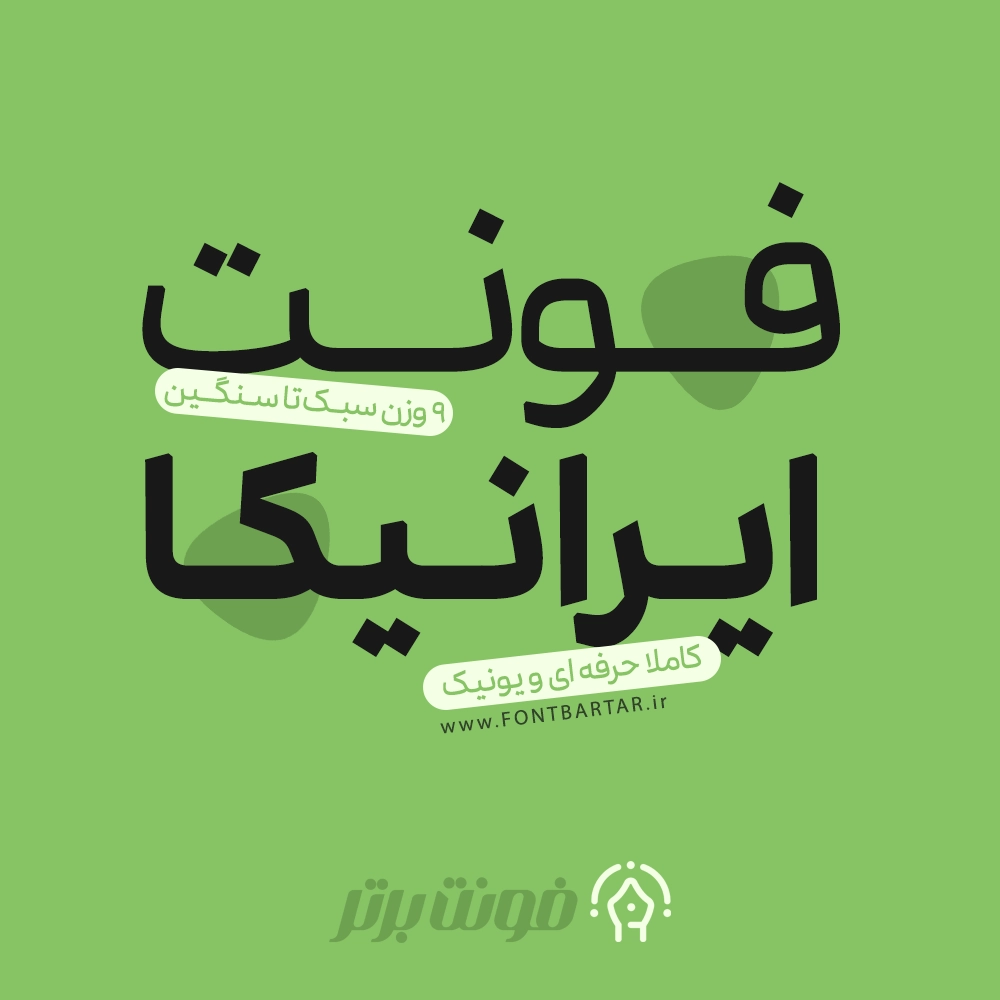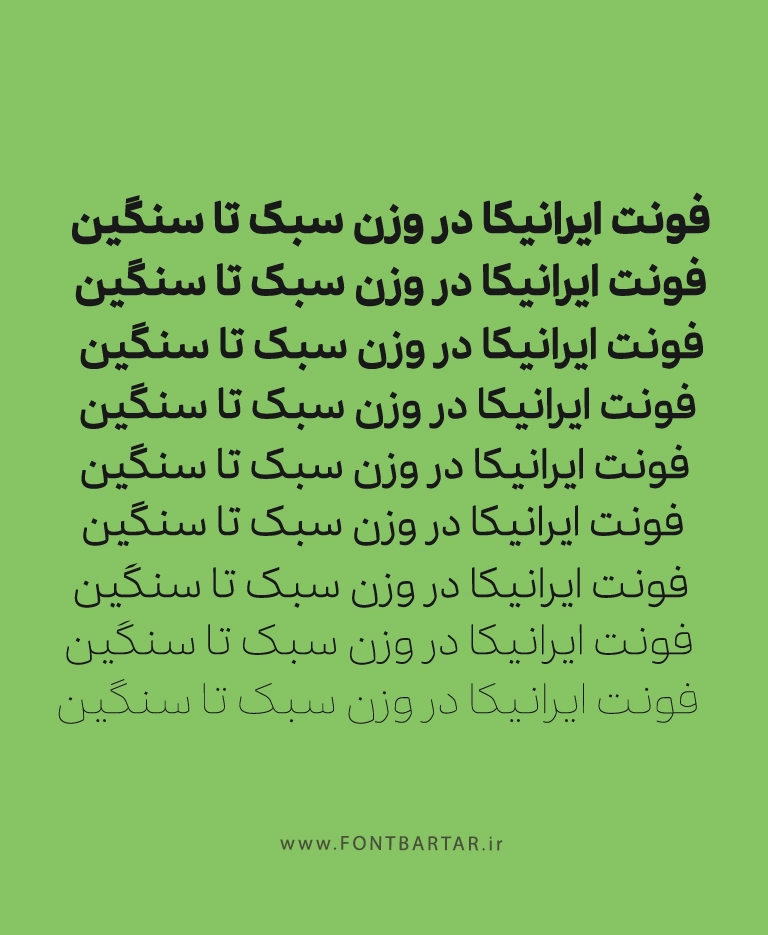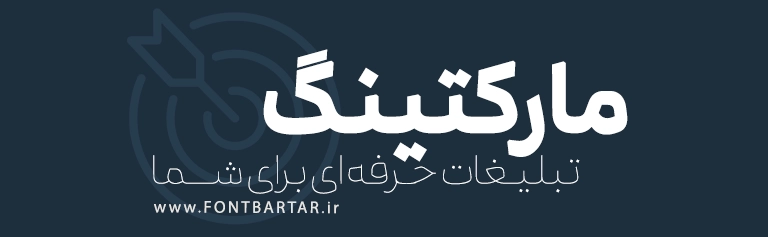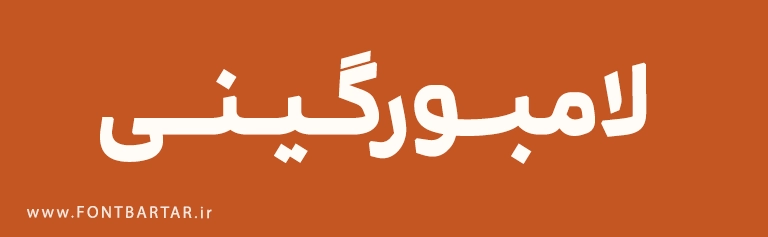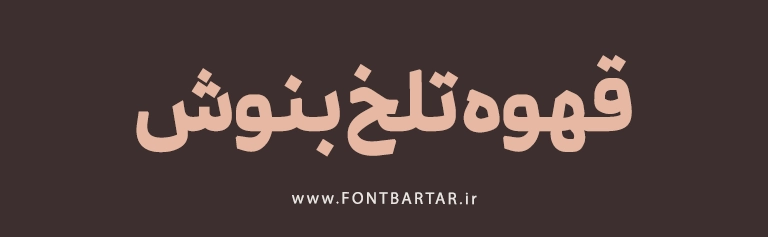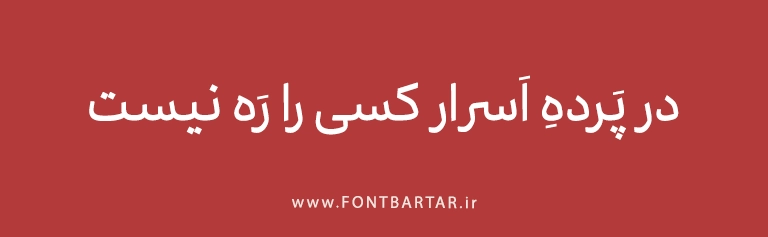
اگر به دنبال یک فونت فارسی قدرتمند، زیبا و چندمنظوره برای پروژههای حرفهای خود هستید، فونت فارسی ایرانیکا یکی از بهترین گزینه هاست. این فونت با طراحی مدرن و ۹ وزن متنوع از سبک تا سنگین، مناسب استفاده در طراحی رابط کاربری، تایپوگرافی، برندینگ، اپلیکیشن، تبلیغات، طراحی پوستر، کاور و حتی صفحات وب است. فونت ایرانیکا می تواند جایگزین جدید برای فونت های فدیمی از جمله فونت ایران یکان ، یکان بخ ، ایران سنس و . . . باشد.
فونت ایرانیکا با ساختار هندسی، خوانایی بالا، فاصلهگذاری هوشمندانه و پشتیبانی از تمام حروف فارسی ، عربی و انگلیسی، انتخابی بینقص برای طراحان حرفه ای است که به دنبال یک فونت جدید یونیک، کامل و استاندارد هستند.
✨ ویژگیهای برجسته فونت ایرانیکا:
- خرید فونت جدید دارای ۹ وزن حرفهای از ExtraLight تا Black
- پشتیبانی کامل از حروف فارسی و انگلیسی
- مناسب برای طراحی لوگو، کاور، پوستر، UI، تبلیغات، مجله و وبسایت
- طراحی مهندسیشده بر اساس اصول تایپوگرافی مدرن
- فونت جدید فارسی فونت یونیک و اختصاصی، بدون مشابه فارسی
فونت زیبا ایرانیکا در 9 وزن سبک تا سنگین:
🎯 چرا فونت ایرانیکا را انتخاب کنیم؟
- فونتی با شخصیت، مناسب برای برندهای حرفهای
- فونت زیبا فارسی جلوهای مدرن و تمیز در طراحی گرافیک
- وضوح بالا در اندازههای کوچک و بزرگ
- مناسب برای متون طولانی، تیتر، لوگو و محتواهای دیجیتال
❤️ فونت فارسی ایرانیکا مناسب برای چه کسانی است؟
- طراحان گرافیک و وبسایت
- مدیران برند و کسبوکارهای دیجیتال
- تولیدکنندگان محتوا و تبلیغات
- توسعهدهندگان رابط کاربری و اپلیکیشن